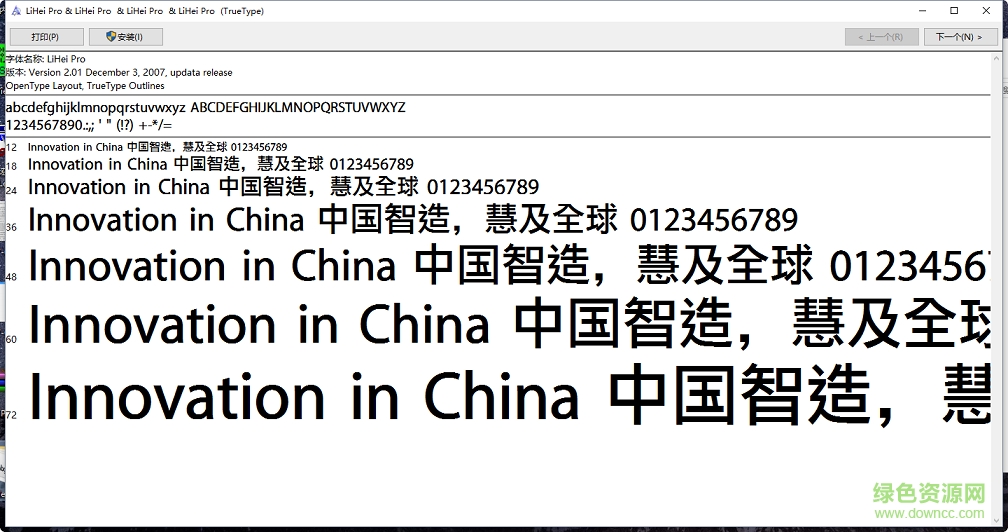
lihei pro字體,中文名稱又叫做麗黑pro字體,是蘋果公司設計的一款非常實用的標準字體,該字體具有現(xiàn)代感的外觀和清晰易讀的效果,線條粗細適中,整體風格非常的出色,并且字庫完整,可用于藝術設計、包裝印刷、簽名設計、圖形設計等領域,有喜歡的朋友可免費下載收藏。
lihei pro簡潔美觀、優(yōu)雅大方。